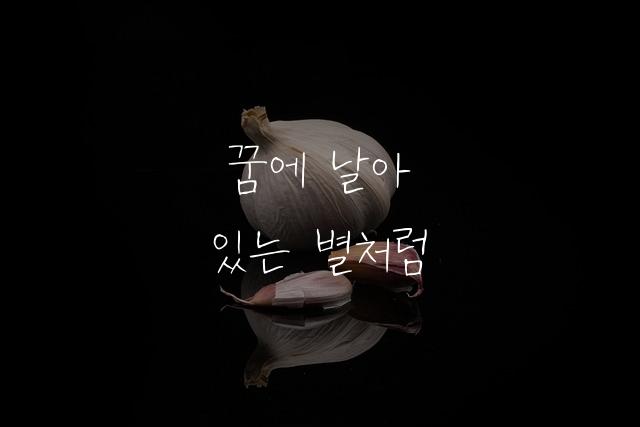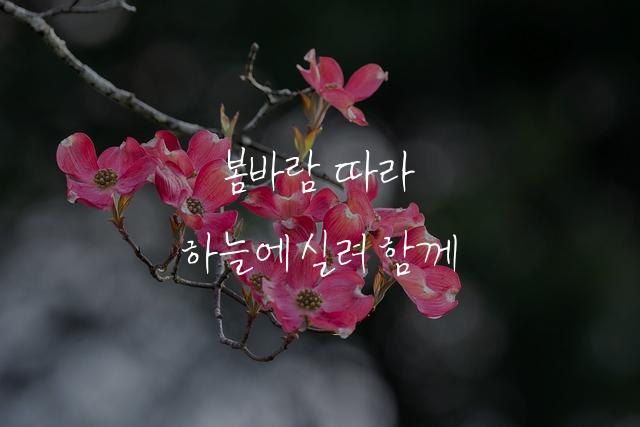
안될과학 유니랩장체는 온글잎과 안될과학의 협업으로 탄생한 독특한 서체입니다. 펜으로 쓴 듯한 동글동글한 글씨가 특징으로, 친근하고 따뜻한 분위기를 자아냅니다.
안될과학 유니랩장체은(는)
둥근 스타일, 펜/붓터치, 감성적인, 자연감성, 부드러움, 복실복실 계열의 생김새를 가지고 있으며
웹/앱 디자인, 보고서/문서 등에서 자주 활용되며, 효과적인 메시지 전달에 적합합니다.
이 폰트는 크리에이티브, 기술/IT 분야에 잘 어울리며,
창의적인, 전문적인 느낌을 담고 있는 것이 특징입니다.
이 폰트와 유사한 폰트로는 나눔손글씨 펜, 바른손글씨, 코리아타이포 손글씨체 등이 있어요. 함께 비교해 보시면 좋습니다!